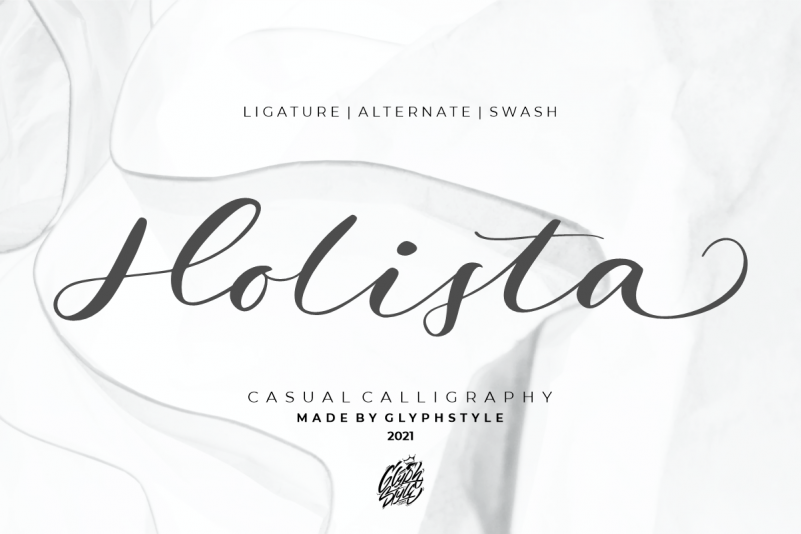
Holista Font – Download Grátis
Esta fonte é perfeita para quem deseja adicionar uma dose extra de elegância ao seu design com estilo de escrita livre. Ela é uma tipografia casual com traços grossos e finos consistentes, criando um ar elegante e encantador que se adapta perfeitamente a textos mais elaborados ou simplesmente decorativos. Criada pelo designer GlyphStyle, esta fonte serve como uma excelente escolha para quem busca estilo sofisticado em seus projetos de design gráfico, seja para trabalhos manuscritos ou para adicionar um toque único aos materiais digitais.